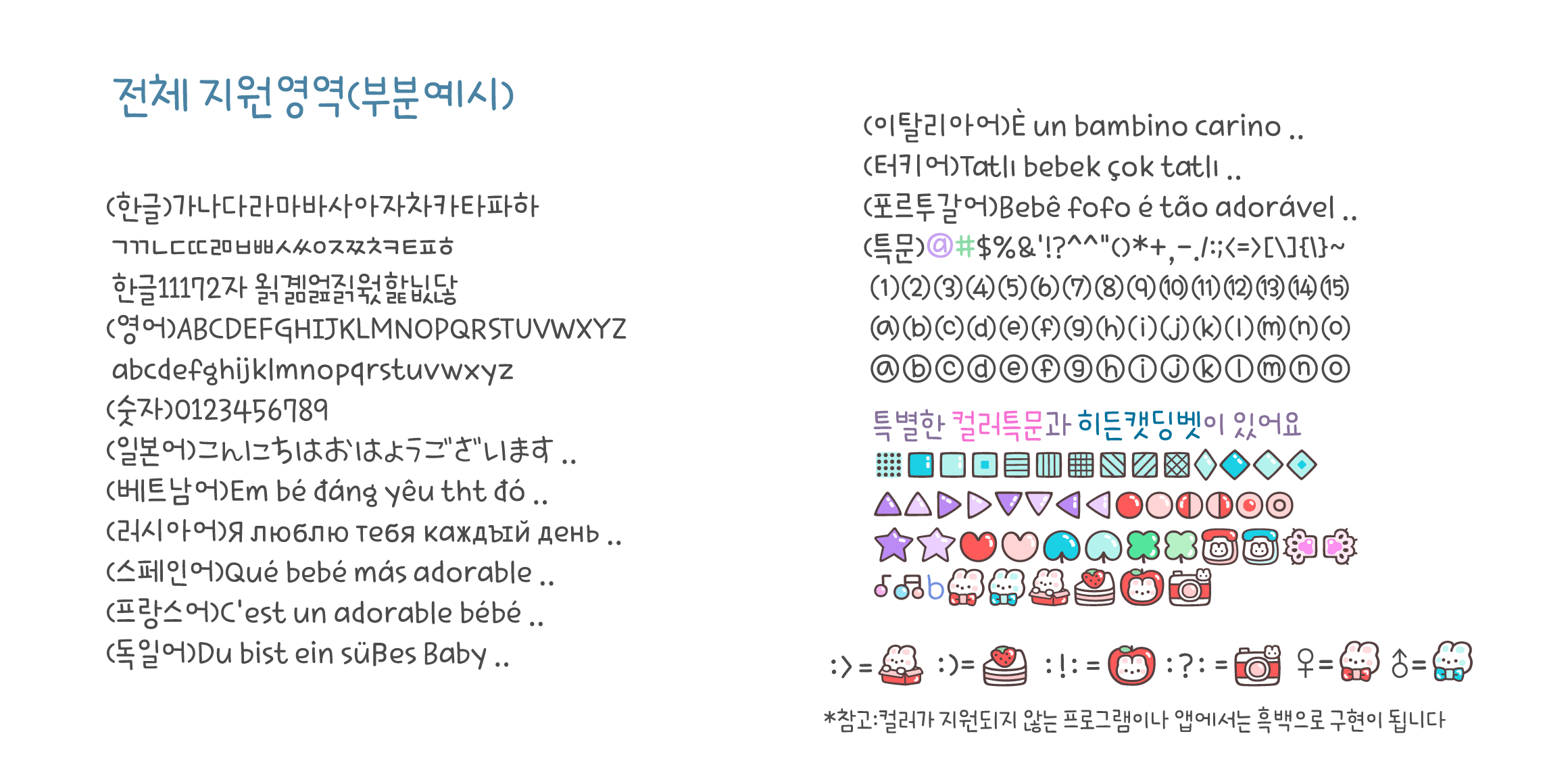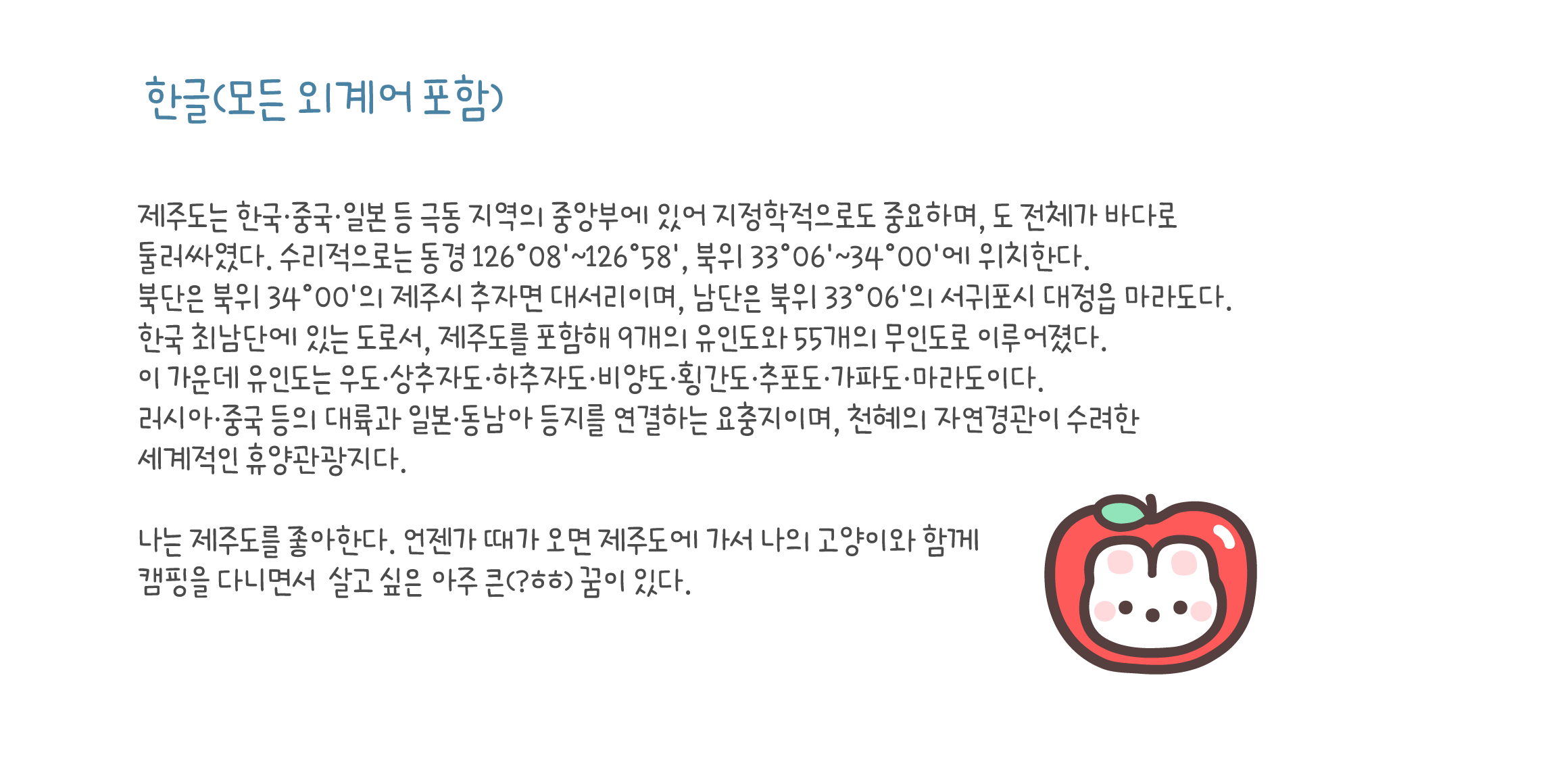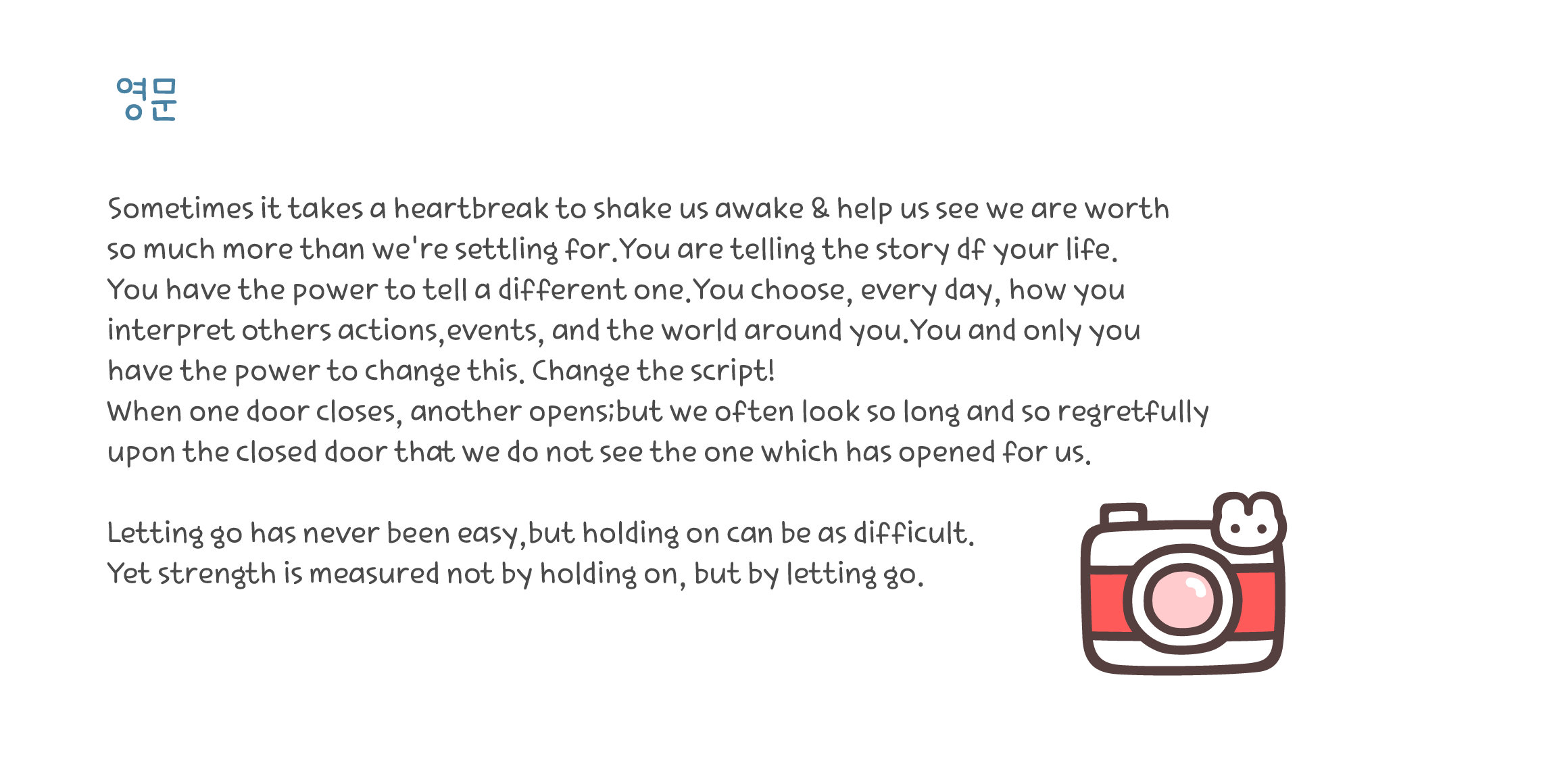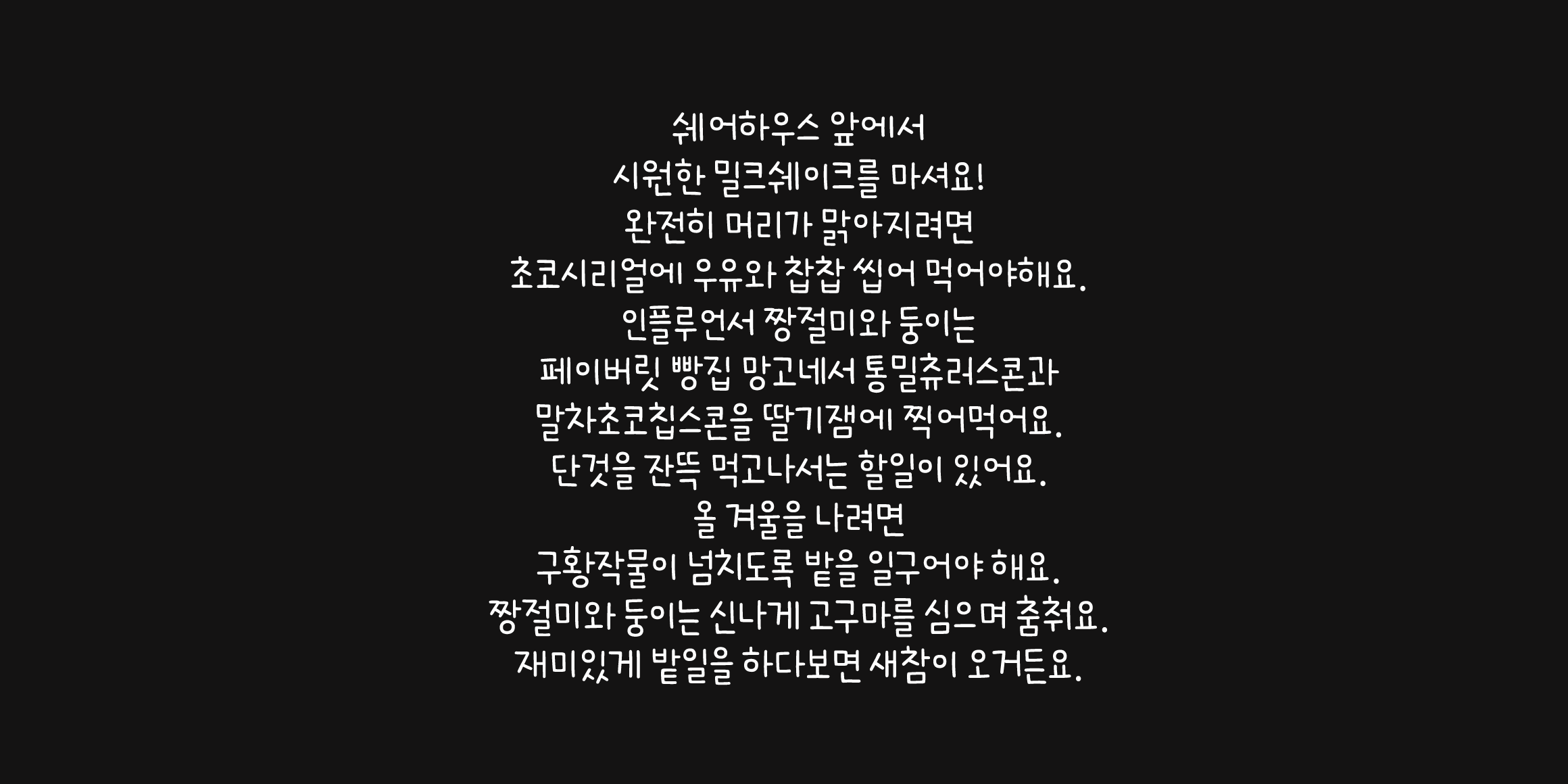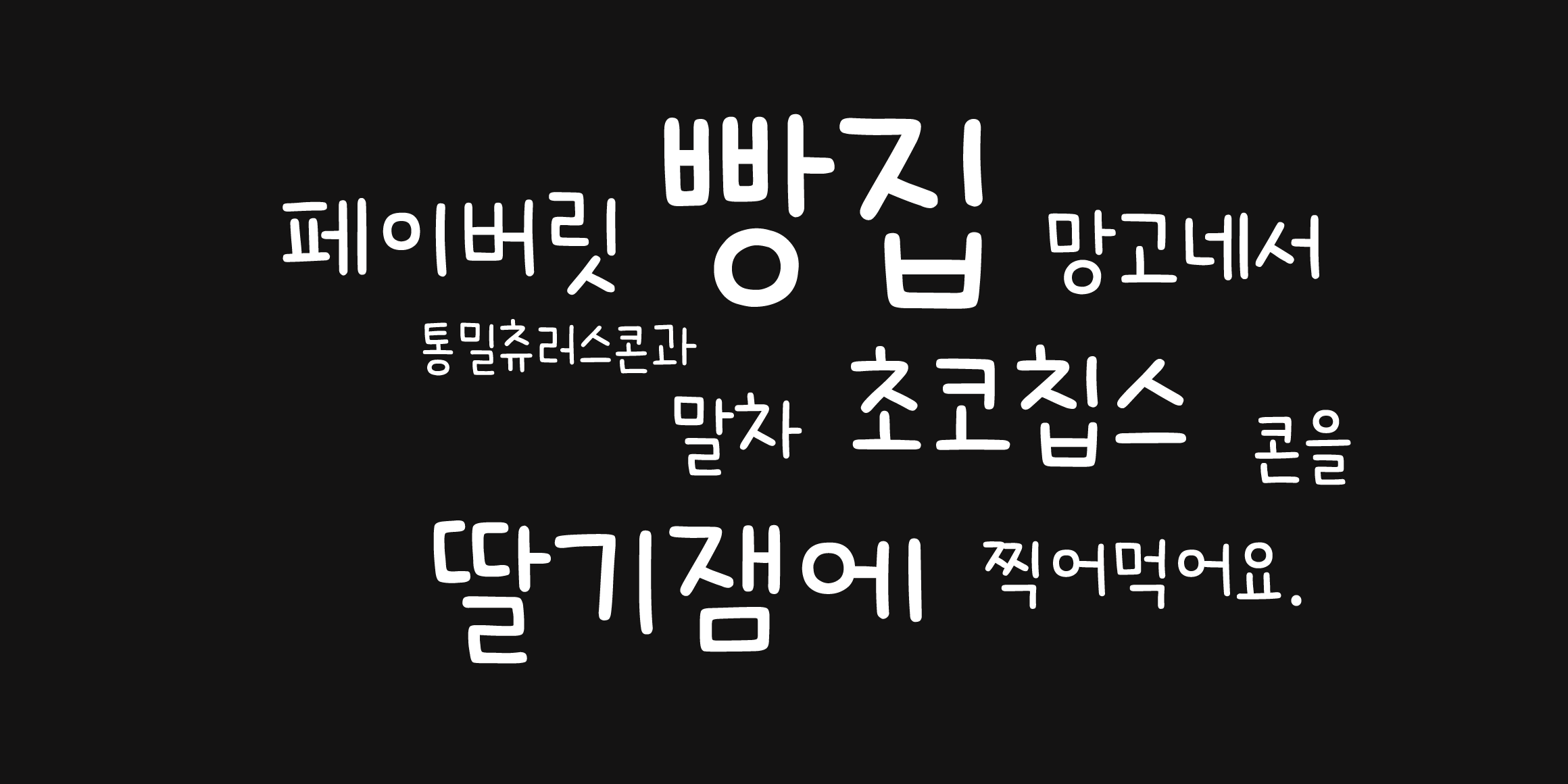
토끼는 딸기케잌을 먹지 않지만,
상큼하고 귀여운 느낌의 둘의 조합을 폰트로 풀어내는 과정은
정말 괜찮은 것 같아요!
♥키보드 ; > ; ) : ! : : ? : 을 연달아 치면
매력적인 캣딩벳이 나타납니다.
♥영어 일어 베트남어를 포함한
독일 프랑스 러시아 이탈리아 포르투갈 스페인 터키 등
유럽의 다양한 국가들의 언어도 함께 지원하는 등
폭넓은 언어와 특수문자 지원을 합니다.
♥캣폰트의 디자인은 오랜 시간 연구한 결과물입니다.
*컬러가 들어간 글자들은 두껍게(Bold)처리를 해도 두께 변화가 없습니다.
- Cat2토끼와딸기케잌 / Cat2BunnyStrawberrycake